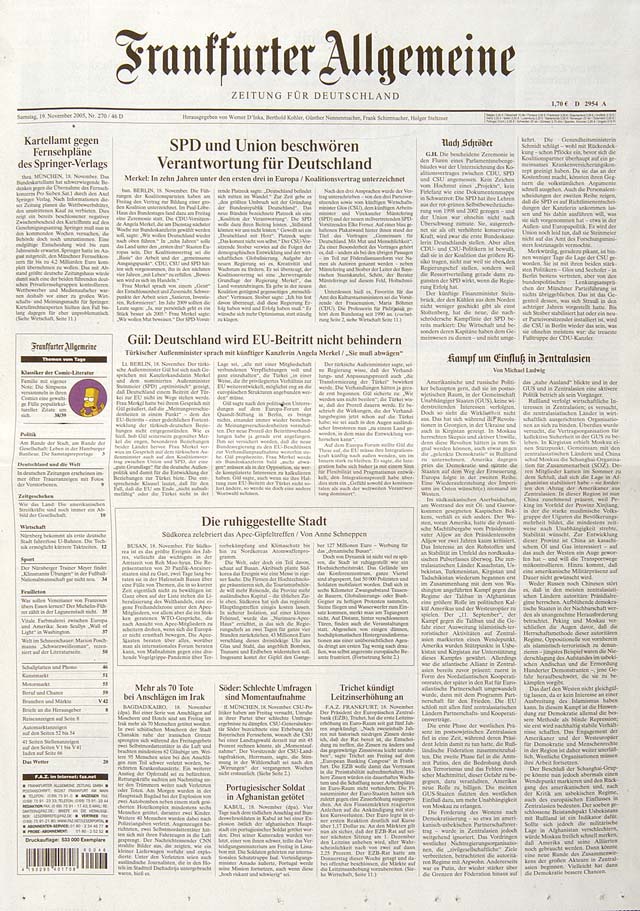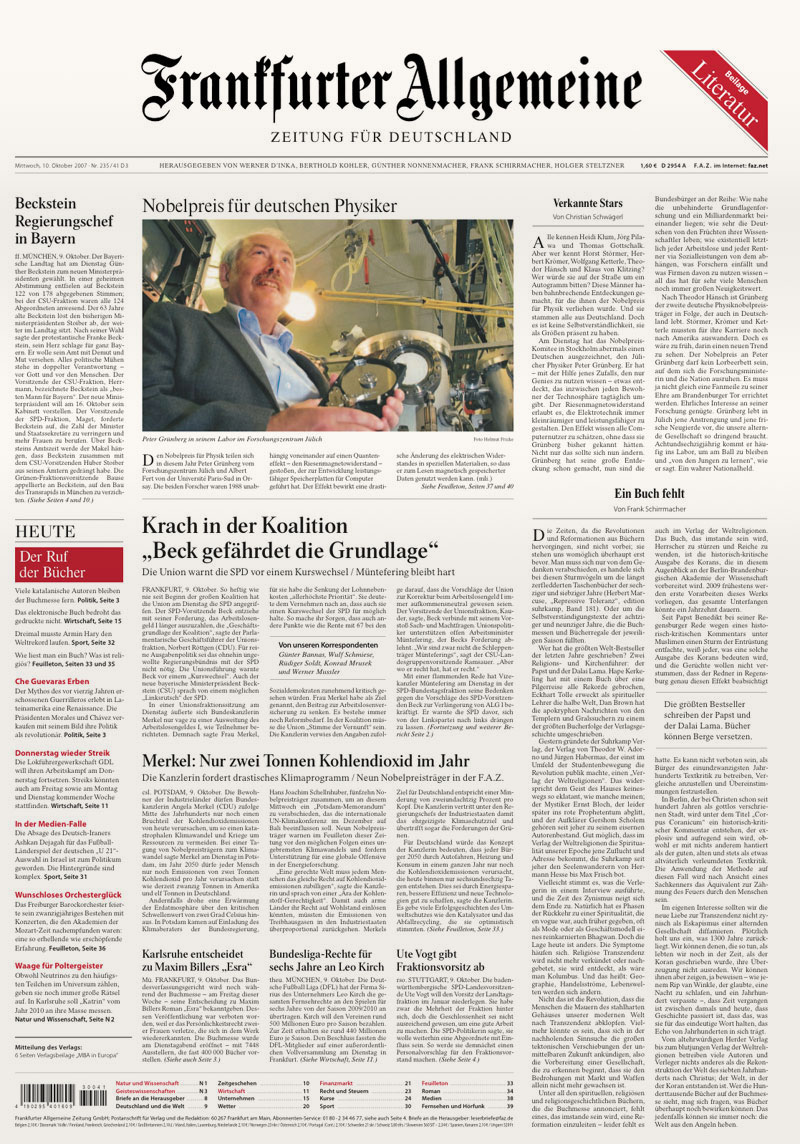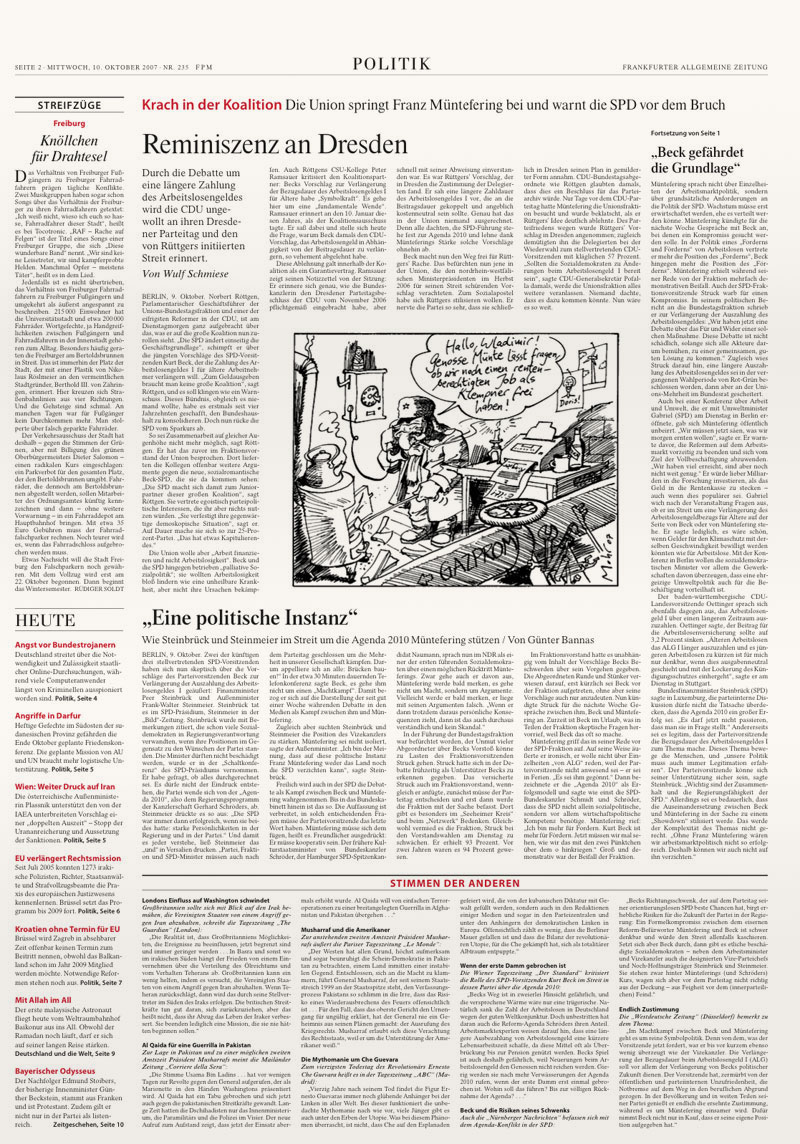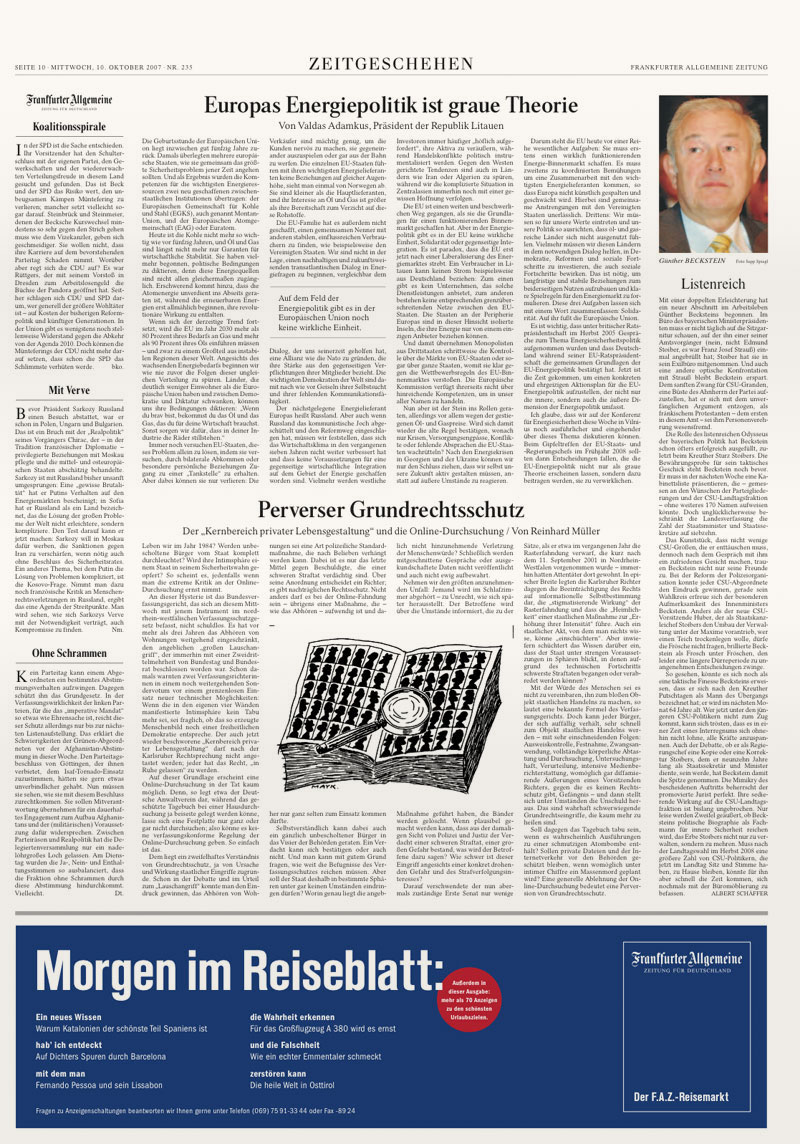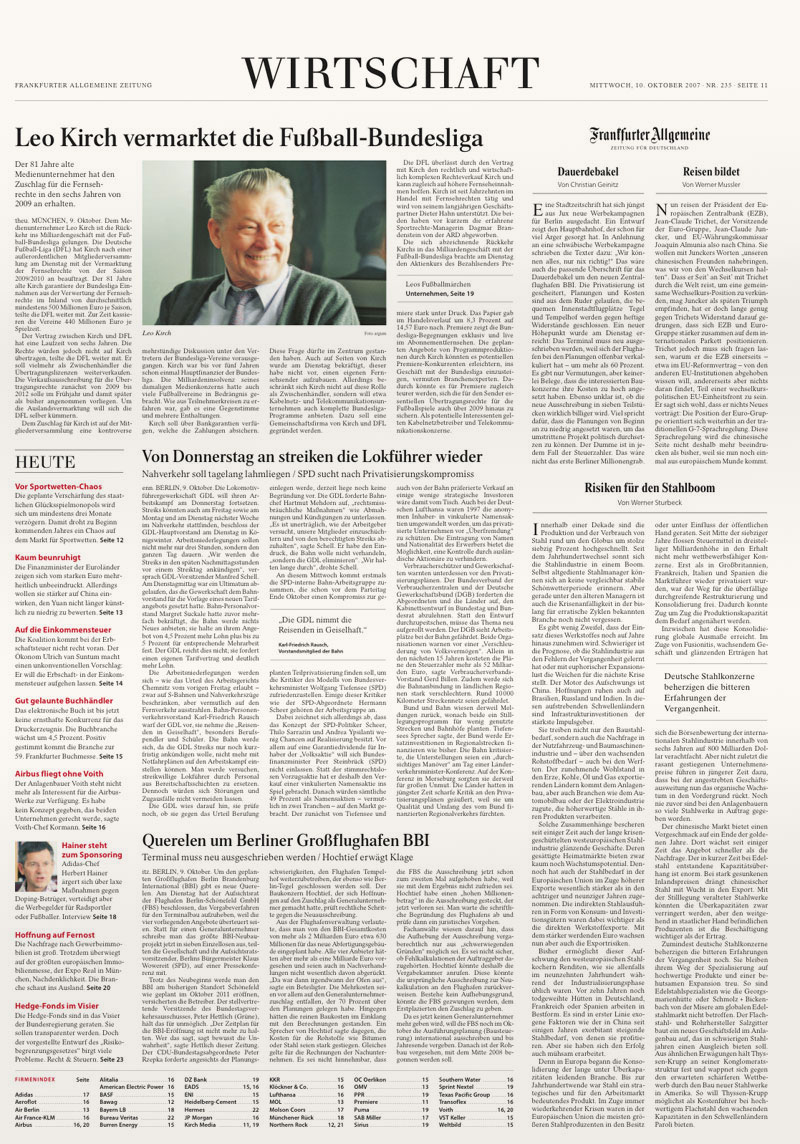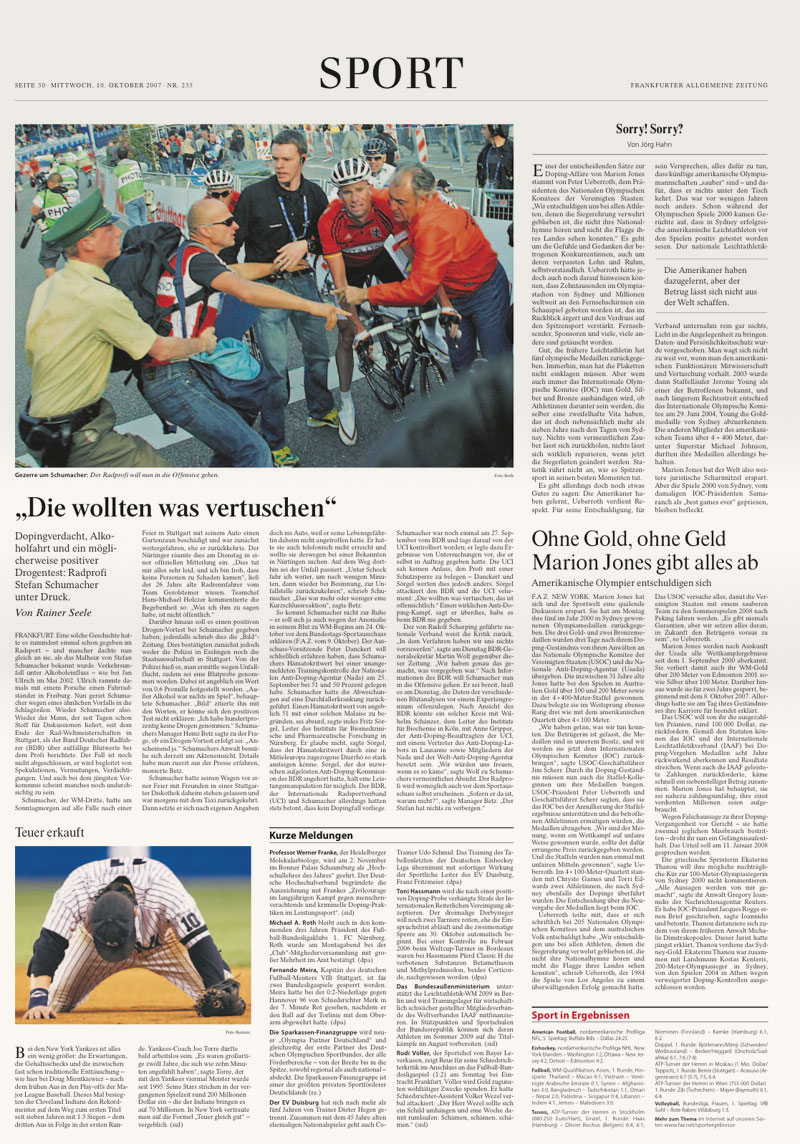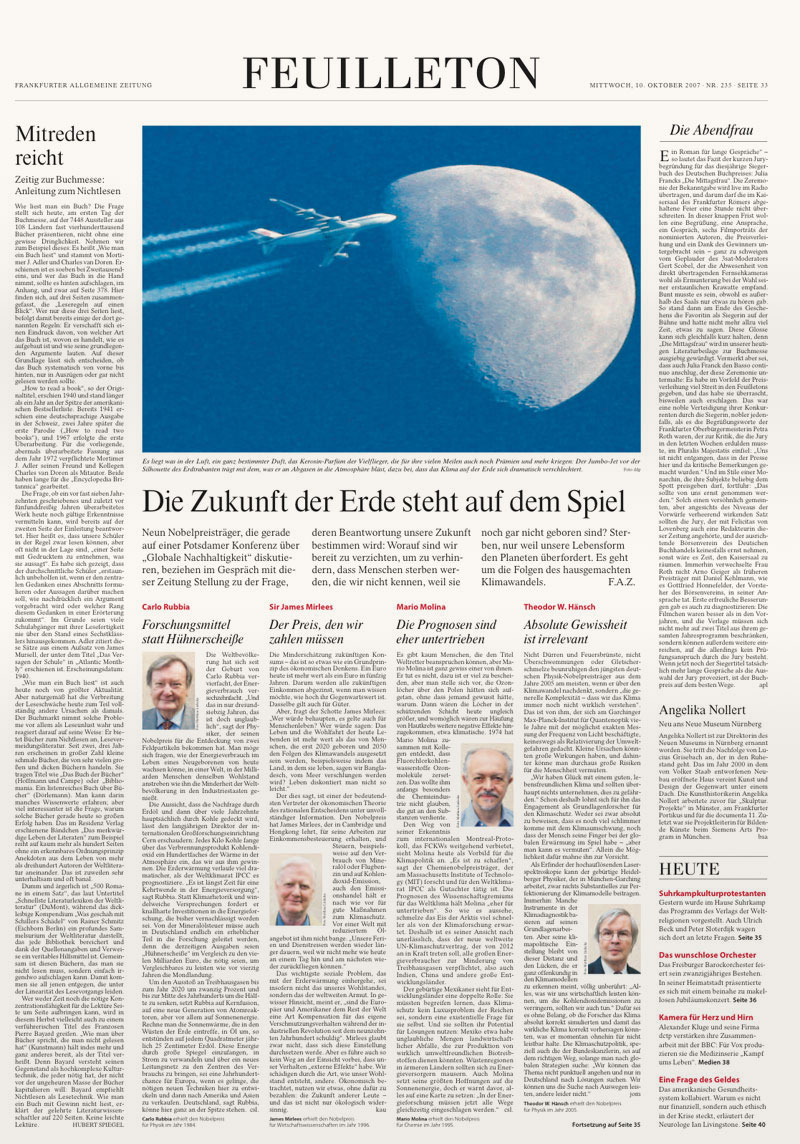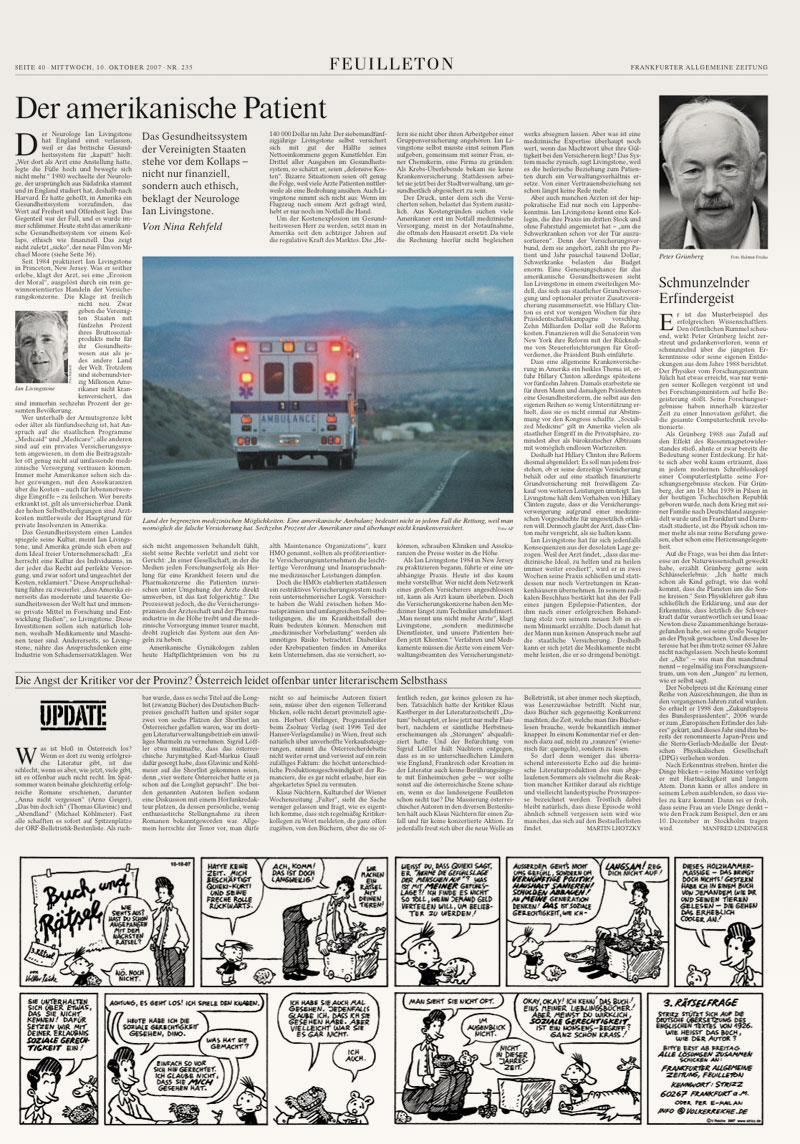
Frankfurter Allgemeine | new design | changement ou continuité?
Voici deux ans j’avais abordé la question épineuse de l’évolution de la presse quotidienne… (1), (2). Comparé déjà le Figaro, le Monde, Libération et puis j’avais cité l’exemple de ce grand journal Allemand le FAZ (Frankfurter Allgemeine Zeitung) qui avec une mise en page sur six colonnes, extraordinairement austère puisque les images en étaient absentes faisait figure d’un monastère au milieu d’un doux «bordel» organisé dans les autres supports de la presse Quot. Mais c’était il y a deux ans, et les choses évoluent vite en ces temps, rudes où partout dans le monde les patrons de Presse se posent la question de leur avenir face au modèle économique 1) du gratuit, 2) de l’information en ligne.
Les sénateurs s’y collent de même, un article dans le Monde daté du 10 (hier) octobre révèle que les sénateurs se sont réunis en commission (Théodule) pour je cite :
“Les sénateurs sont partis du constat que «  la presse quotidienne est en danger », confrontée à la baisse continue des recettes et au maintien de coûts de production élevés. Autant d’éléments qui font de la presse quotidienne nationale (PQN) un secteur peu rentable. La concurrence est farouche, notamment avec l’arrivée des quotidiens gratuits, et les éditeurs doivent bâtir une stratégie sur le numérique.”
Mon dieu, ça fait un bail que la Presse Quot est en danger en France et pas seulement… Les difficultés de cette presse remonte aux années 60 lorsque déjà les tirages commençaient à décliner. Mais il est vrai que de reflux lent et persistant on est passé à une véritable débâcle…
«La baisse continue des recettes…» entendez par là la concurrence du village global des médias McLuhanien, c’est à dire électroniques… Radio, Télé, Internet, et évidemment bientôt, aujourd’hui, les mobiles…
«Le maintien des coûts de production élevée…» là il faut lire entre les lignes… Les coûts de production de la Presse comme de l’ensemble des métiers de l’Edition ont été divisés par 3 ou 4 depuis 15 ans. L’arrivée des process de production du numérique a grandement profité à l’industrie de la Presse… économies sur la circulation du «papier» qui passe directement du journaliste, au SR et sur l’ordinateur de la salle de montage de la maquette pour finir sur l’ordinateur qui va amalgamer les pages (imposition) et les graver au laser sur les plaques offset des rotatives (plus de films).
Systèmes éditoriaux efficaces qui au final ont bien changé (et réduit) le métier d’une époque où l’on allait «au marbre» pour contrôler une dernière fois les «morasse» sortis fraîchement de la presse à épreuve… Oui les coûts de production aussi bien à la typographie (du plomb au numérique) que sur les rotatives et la distribution des données pour l’impression en Presse Régionale ont été lourdement divisés par 3 ou 4…
Les seuls coûts (et encore) à être restés constants, ceux de la rédaction, des journalistes aux dirigeants se recyclent depuis quelques années (l’arrivée du haut débit) dans les compléments internet de cette presse quot. Se faisant, on peut aussi supposer que le modèle économique futur n’est pas si «impossible» ou «intenable» que cela. Reste bien sûr les droits associés à l’écriture des papiers, et à définir leur circulation maîtrisée en terme juridique et comptable. Mais l’on ne s’en fait pas trop. Les experts et syndicats sauront trouver les bonnes formules…
Si donc on ne devrait pas trop s’en faire sur les coûts, on peut alors s’intérroger sur la Vente des journaux quotidiens. D’aucuns disent qu’elle est liée au prix exorbitant, 1,50 euros en moyenne, et de proposer qui, des subventions, qui, des baisses vis à vis des étudiants… mais cela se pratique déjà. Dans bon nombre d’écoles, des journaux comme Libération ou Le Monde sont soit distribués gratuitement soit vendus avec des prix au rabais importants. Cela ne conforte pas le modèle économique mais empêche la désaffection au média.
Il faut je crois se pencher sérieusement sur cette maquette du Frankfurter pour comprendre les ressorts d’un maintien sinon d’un redéploiement de la presse écrite.
Composé déjà sur six colonnes avant le relooking et toujours sur six colonnes après, on ne distingue guère beaucoup de différence et ce n’est certes pas la suppression des filets verticaux séparateurs qui fondent une révolution visuelle.
L’éditing des titres et inter-titres gagne en contemporanité avec un mode de composition en «fer à gauche», et une force typographique nettement plus visible (mais pas plus lisible), ce qui confère à l’ensemble un rythme graphique plus marqué par les oppositions des valeurs de noir des titres et du gris des textes. Ces derniers toujours composés toujours avec autant de minutie ne laisse pas de m’enchanter par leur gris maîtrisé et l’on reconnaît bien là, la sensibilité typographique allemande qui ne supporte pas trop les lézardes et autres rivières chers à nos quotidiens français.
En conclusion ce qui fondait la notoriété principale du journal de Frankfurt, la longueur des articles, le peu de cas des relances de lectures, l’impression générale «qu’il faut y aller», «qu’il faut se tartiner de la lecture laborieuse» parce que rien n’est prévu pour une lecture rapide «en diagonale» de cette presse, qui traite les sujets «au fond» et pas dans la précipitation d’une actualité en devenir permanent, cette impression générale donc reste constant.
Plus intéressant l’introduction de la photographie dans la nouvelle maquette.
L’ancienne formule du FAZ
La Une de la nouvelle formule